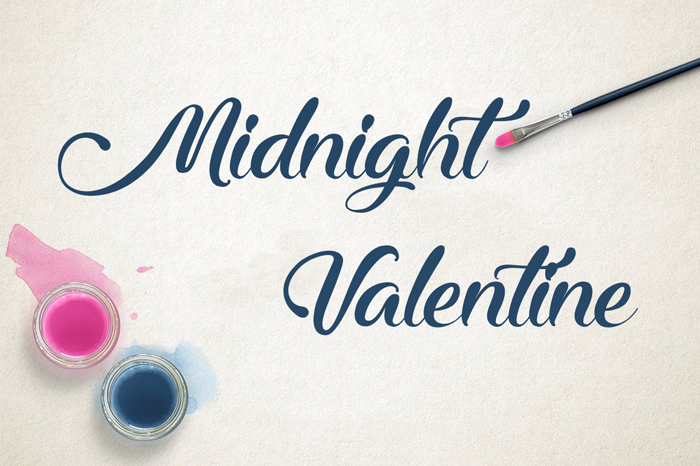
Midnight Valentine Font – Download Grátis
A Midnight Valentine Font é uma deliciosa mistura de elegância e originalidade, perfeitamente adaptada para qualquer projeto que exige um toque especial de arte. Desenvolvida pelo criativo Octotype, esta fonte chama a atenção por seu aspecto delicado e atrevido ao mesmo tempo. Ideal para designers apaixonados por escrita filigranada, ela oferece uma variedade de linhas finas e garridas que se adequam perfeitamente a qualquer projeto de design gráfico ou impressão. Com uma licença comercial completa disponível no site , você pode explorar as infinitas possibilidades dessa fonte única. Seja para criar materiais promocionais, ilustrações singulares ou até mesmo textos com um toque especial, a Midnight Valentine é a escolha perfeita. Acessível e versátil, ela está aqui para revolucionar seu design.